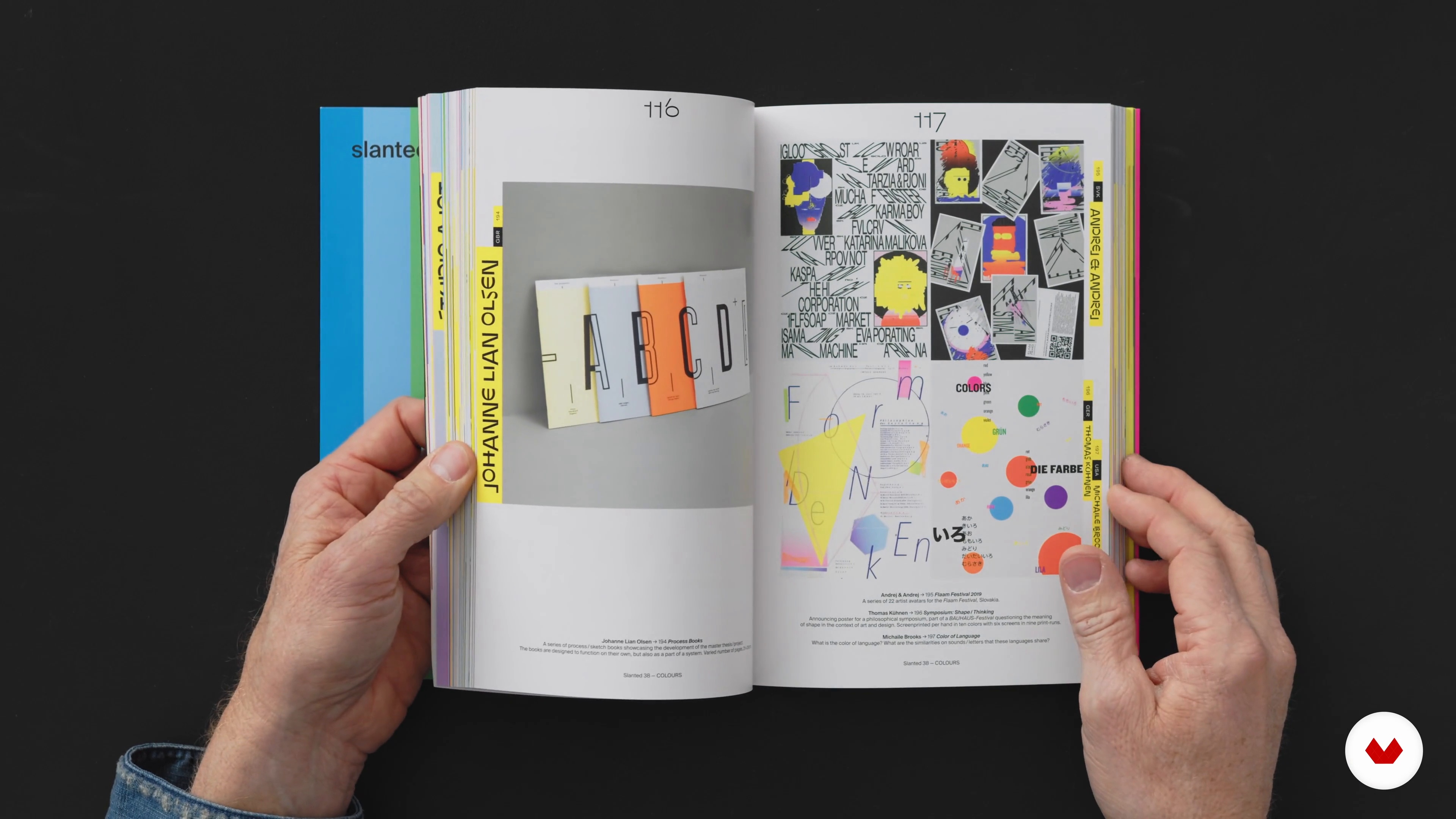
Eléments graphiques : illustration, typographie et graphisme
“Un élément important et un outil de la conception est la typographie. Le travail du typographe est de bien combiner micro-typographie et macro-typographie. Je pourrais proposer toute une unité de cours à titre d'illustration, mais cela dépasserait le cadre. Néanmoins, j'aimerais donner une place à cet élément important du design d'un magazine. ”
Dans cette leçon, Lars Harmsen aborde le sujet : Eléments graphiques : illustration, typographie et graphisme, qui fait partie du cours Domestika en ligne : Design éditorial : donnez vie à une publication. Découvrez le processus de création d’une revue ou d’un magazine avec le fondateur de Slanted Publishers et apprenez à raconter des histoires à travers la couleur, la typographie et la mise en page.
“Illustration d'éléments graphiques, typographie et graphisme Salut. Ce chapitre traite de la typographie, formes graphiques, polices, tous les éléments dont vous avez besoin pour allumer des feux d'artifice dans la conception du magazine. La typographie est déterminée en choisissant les polices. Comme vous l'avez probablement déjà remarqué est-ce un immense terrain de jeu où les graphistes aiment se défouler. Simplement la sélection de superbes polices passionnantes et vu comme ça dans un magazine peut être fait vibrer avec d'autres éléments graphiques. Il s'agissait de trois diapositives d...”